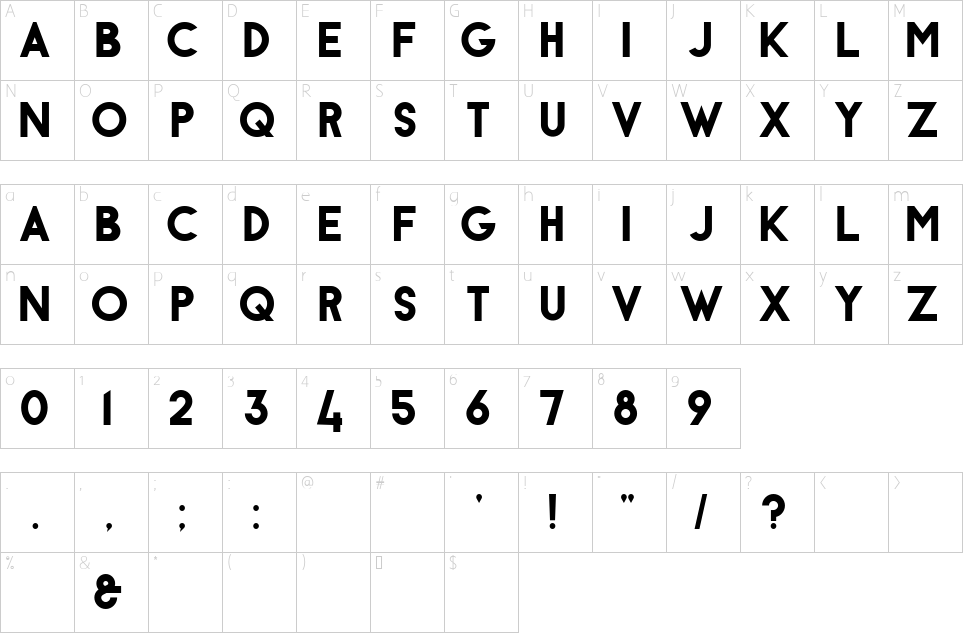
Descubra a beleza única da Antraste font, uma delas para Windows e Mac. Desenvolvida por Marco Ballarè, esta fonte vem para adicionar um toque especial a qualquer projeto gráfico. Com seus traços elegantes e uma proporção harmônica, a Antraste não apenas torna seu trabalho mais profissional, mas também mais atraente. Desde o título de sua página até o texto de corpo, ela é capaz de transformar qualquer design. Seja para criar gráficos, editoriais de web ou qualquer outro tipo de projeto, Antraste é uma escolha inteligente. E para quem aprecia a diversidade e qualidade de uma fonte gratuita, essa é uma fonte maravilhosa para experimentar. Com um estilo clássico que se destaca, Antraste é mais do que uma fonte, é um detalhe que irá aprimorar sua criação.